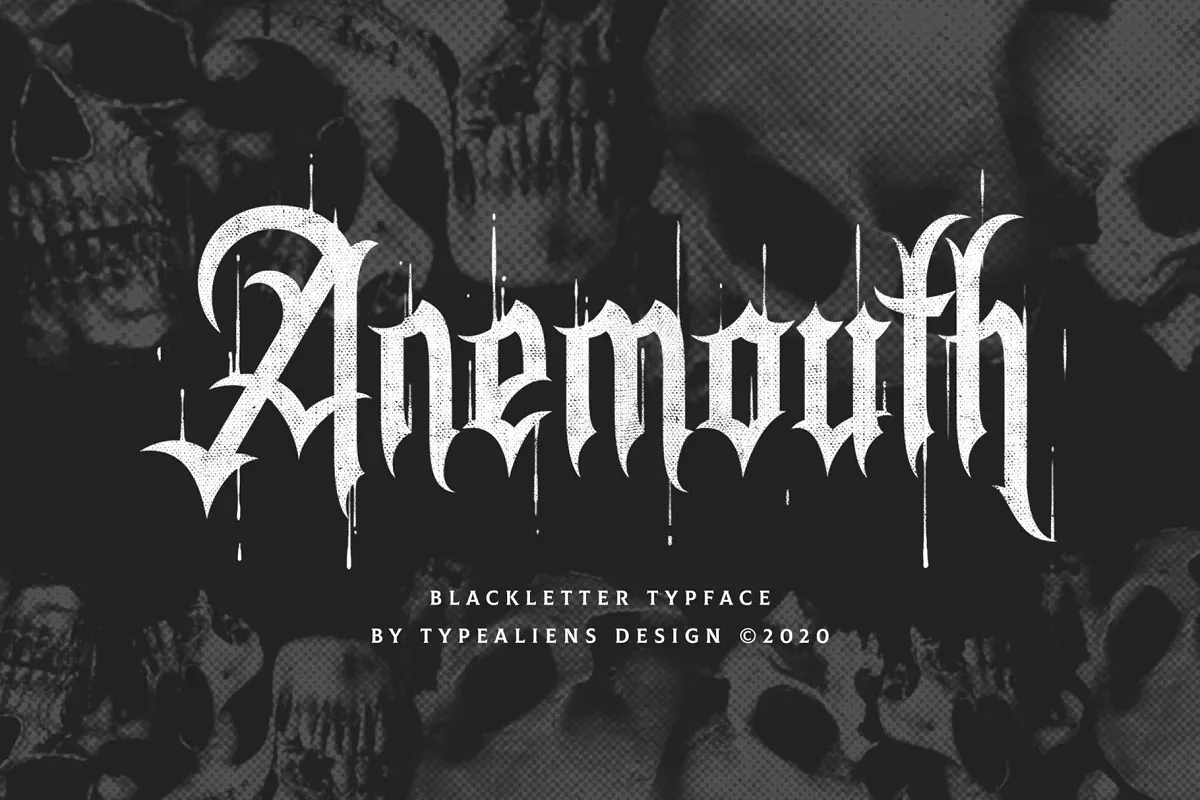
Anemouth Font – Fonte Grátis
Anemouth Font
A Anemouth Font é uma escolha perfeita para os amantes do estilo Blackletter que buscam uma conexão direta com a cultura da antiguidade enquanto mantém seu olhar atento ao futuro moderno. Inspirada no velho estilo gótico conhecido como letra negra, esta fonte traz um toque de vitalidade à tradicional tipografia clássica. Não é apenas uma recriação exata do passado; ela evolui e se adapta com facilidade para combinar perfeitamente com os ambientes digitais atuais. Em um mundo que rapidamente transforma-se, a Anemouth Font oferece uma conexão única entre o legado dos velhos padrões de escrita e as inovações do design contemporâneo. Seja para marcar capítulos históricos ou assinar documentos futuristas, esta fonte Blackletter é um artefato ideal que não apenas preserva a força do passado, mas também reflete a sua versatilidade moderna.